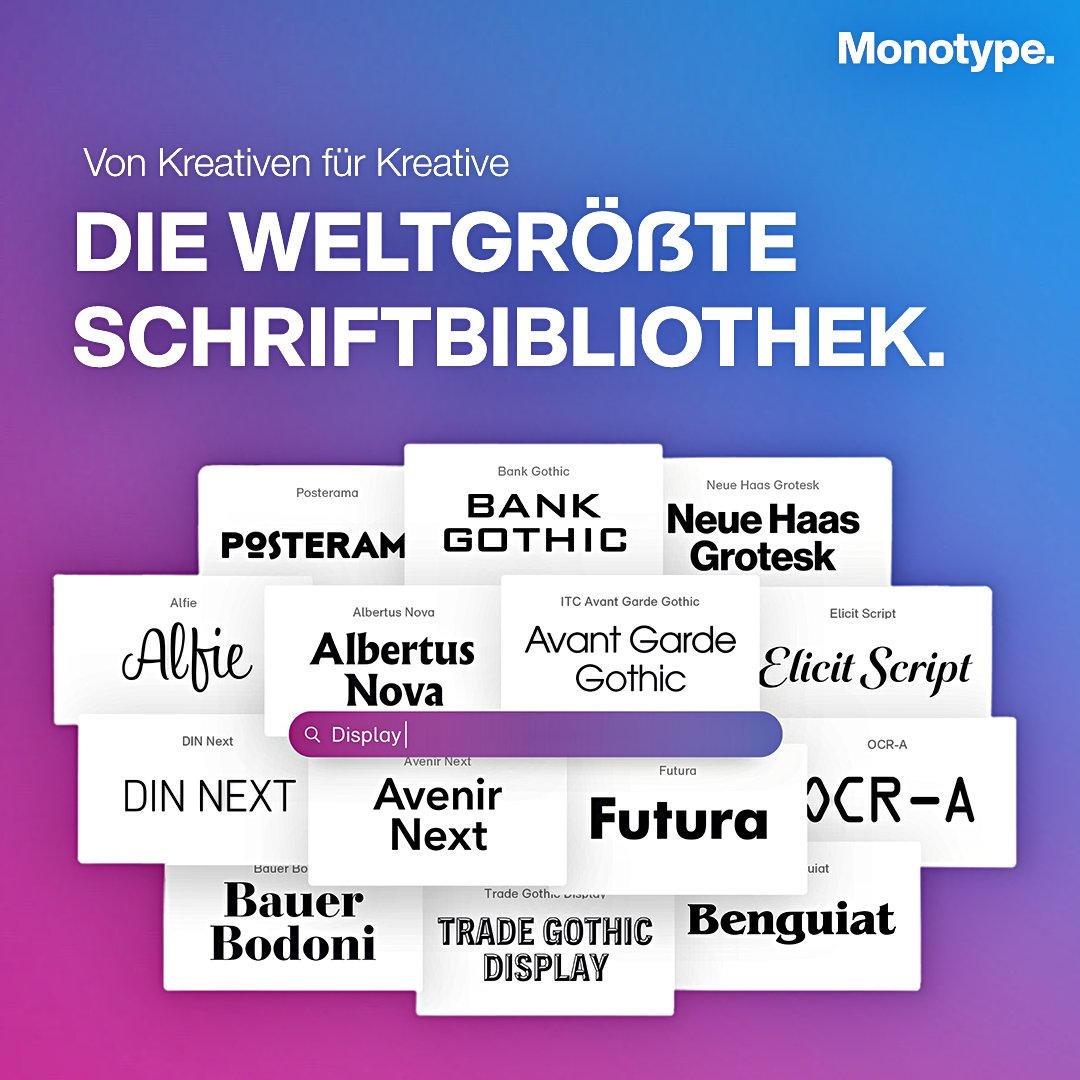
Etwas ungewöhnlich, aber trotzdem schön, dass Ihr daran gedacht habt! Vielleicht sollte man diese Erklärung auch in die Wiki-Einträge übernehmen. Bis jetzt sind wir hier davon ausgegangen, dass das ẞ in den Fonts gar nicht existiert.
Vielleicht kann noch jemand den Eintrag für die FF DIN Round machen? :-)
Da Ralf gerne Bilder der Schrift hat (insbesondere des a), wäre es gut, wenn jemand den Artikel erstellt, der auch über die Schriften verfügt, damit keiner in Copyright-Probleme reinrennt.
Oder dürfen wir die Voransichten von Myfonts einfach so verwenden @Ralf Herrmann?
ist es euch schon aufgefallen? seit kurzem setzt apple maps (am iphone und auch am mac) bei den schon immer versal geschriebenen straßennnamen das versal-eszett ein.
Ja, bei mir bisher aber nur am iPhone (und iPad 🤔) … zumindest bis letztens noch nicht am iMac.
Fürcherliches Ding. Ich bin ja generell für weite Eszetts, aber das geht ja auf keine Kuhhaut. Mit dem Kopf gestaltet statt mit dem Auge.
(Ich habe erst mal «heiß» gelesen...)